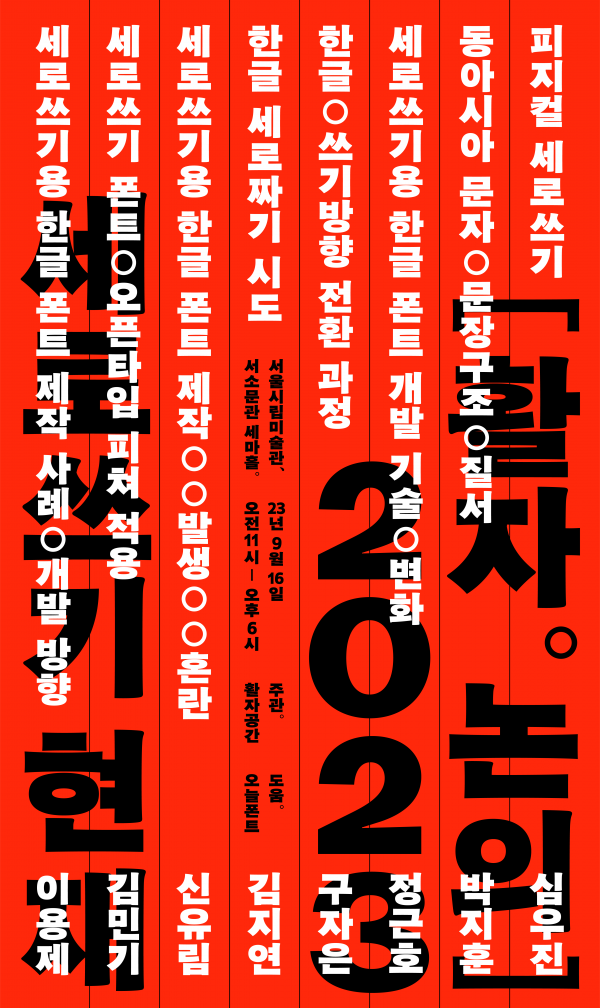
[활자.논의] 2023: 세로쓰기의 현재
'세로쓰기를 다시 시작한지 20년, 지금까지의 세로쓰기를 톺아보다'
1945년을 기점으로, 한글은 세로에서 가로로 쓰기 방향이 바뀌기 시작했으며, 1970년대 전후로, 나라에서 한글 가로쓰기 전용을 추진하면서 세로쓰기는 점차 사라졌다. 그리고 1990년 즈음, 조판 환경이 디지털로 전환되면서, 우리 사회에서 한글 세로짜기는 점점 사라졌고, 2000년 즈음에는 대부분 사라졌다.
세로짜기 맥이 끊어진 몇 년 뒤 세로쓰기 전용 폰트 [꽃길](이용제. 2004~2006)이 개발됐으나, 디지털 환경에서 한글 세로짜기는 불편했을뿐만 아니라, 이미 사회도 가로쓰기가 익숙해져 있었다. 특히 한글 세로쓰기가 비효율적이고 가독성이 낮다는 인식이 널리 퍼져 있었다.
2014년 세로쓰기 전용 한글 폰트 [바람.체](이용제)가 발표될 때에 컴퓨터 환경이 조금씩 개선되면서, 불편하지만 한글을 세로로 쓸 수 있었다. 차츰 한글로 세로짜기를 할 수 있게 되면서, 우리는 일상에서 세로로 쓴 한글을 심심치 않게 볼 수 있게 되었고, 더불어 지난 10년 사이, 세로쓰기용 한글 폰트 제작도 늘어났다.
2023년은 다시 세로쓰기용 한글 폰트를 개발한지 20년이 되는 해다. 그동안 개발된 세로쓰기용 한글 폰트와 그에 관한 연구를 발표한다.